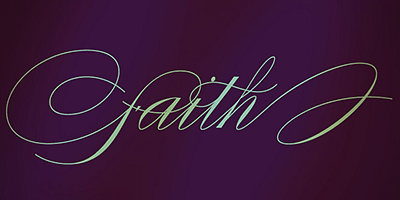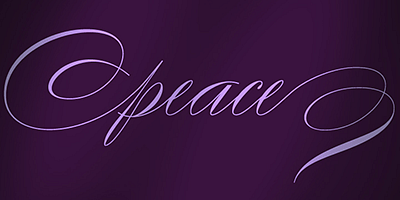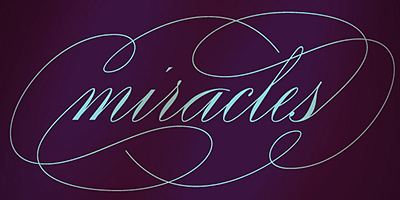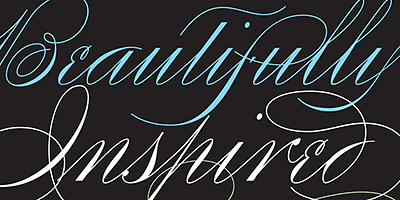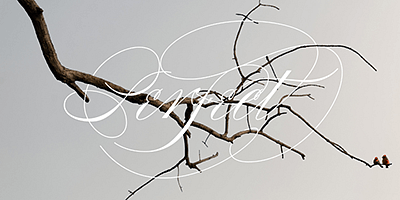
Kompendium är en uppföljare till min font Burgues från 2007. Egentligen kanske man kan kalla det en förföljare till Burgues. Innan Louis Madarasz fick alla i sydöstra USA att tappa hakan med sina disciplinerade hörn och vilda hårstreck hade Platt Rogers Spencer uppe i Ohio skapat sig en helt egen stil, som till slut skulle bli grunden för den avvikande kalligrafiska metod som sedermera konstruerades och utvecklades av Madarasz.